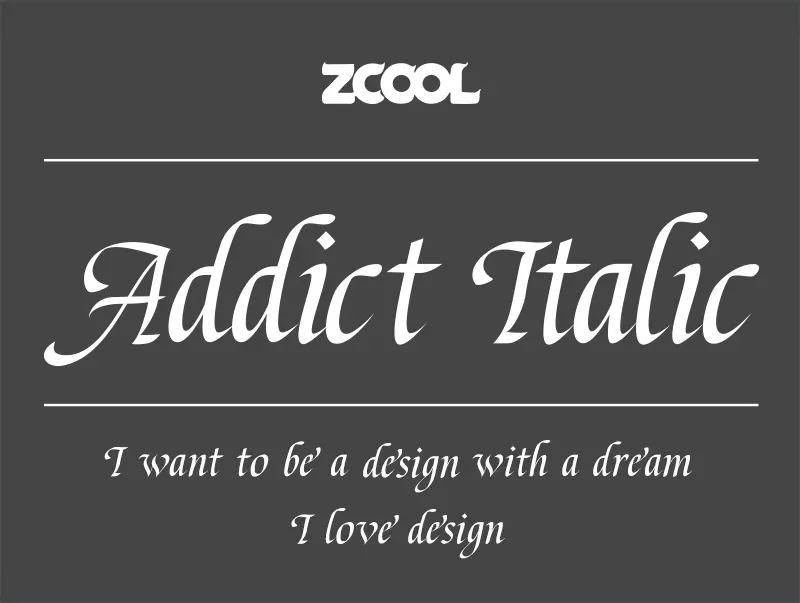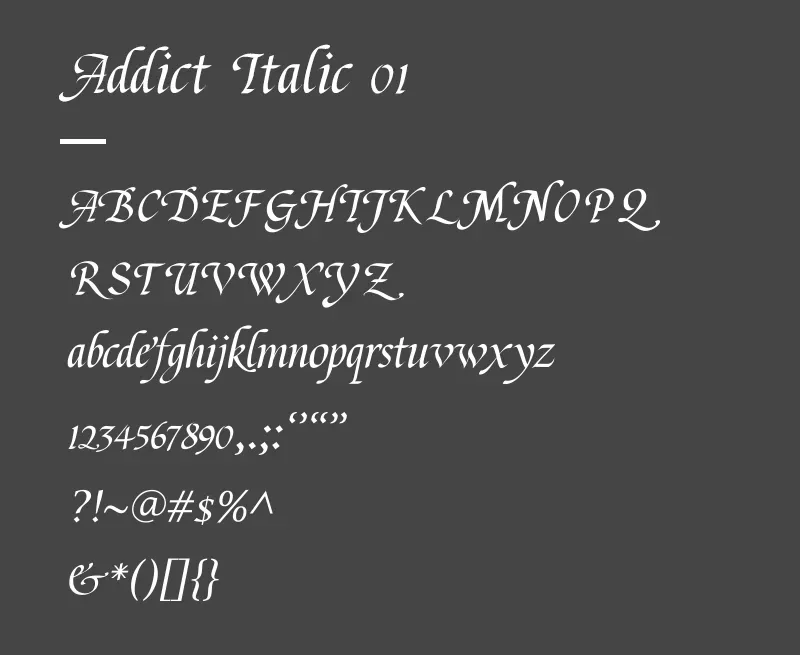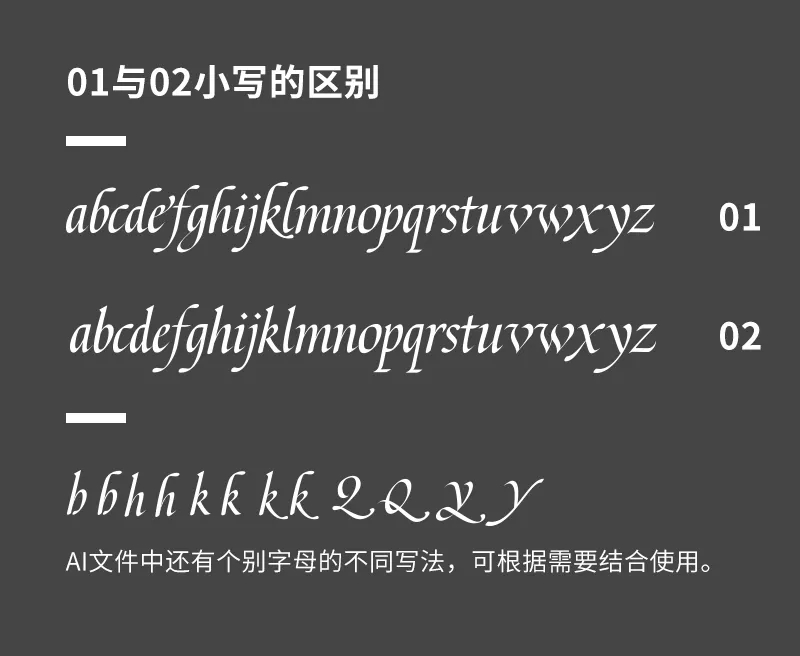
站酷意大利體(ZCOOL Addict Italic)是由大貓Addict設計,站酷冠名的首款公益西文字庫, 52個字母,10個數字,24個符號。是可免費商用的西文字,2016年5月發佈第一版。
關於站酷字體:站酷公益字體,源自2014年的一次公益造字活動。由站酷ZCOOL的活躍字體設計師胡曉波及劉兵克發起這個項目,並設計最初的字形規範及基本部首,其餘字形以眾包的形式由分散在全國的79名設計師分別完成,最終一套好用並且免費的中文字體“站酷高端黑”誕生並在2014年聖誕發佈。自從站酷高端黑之後,有更多的設計師團隊和個人將字體贈送給站酷公益字體項目,交由站酷傳播,給更多設計師使用。